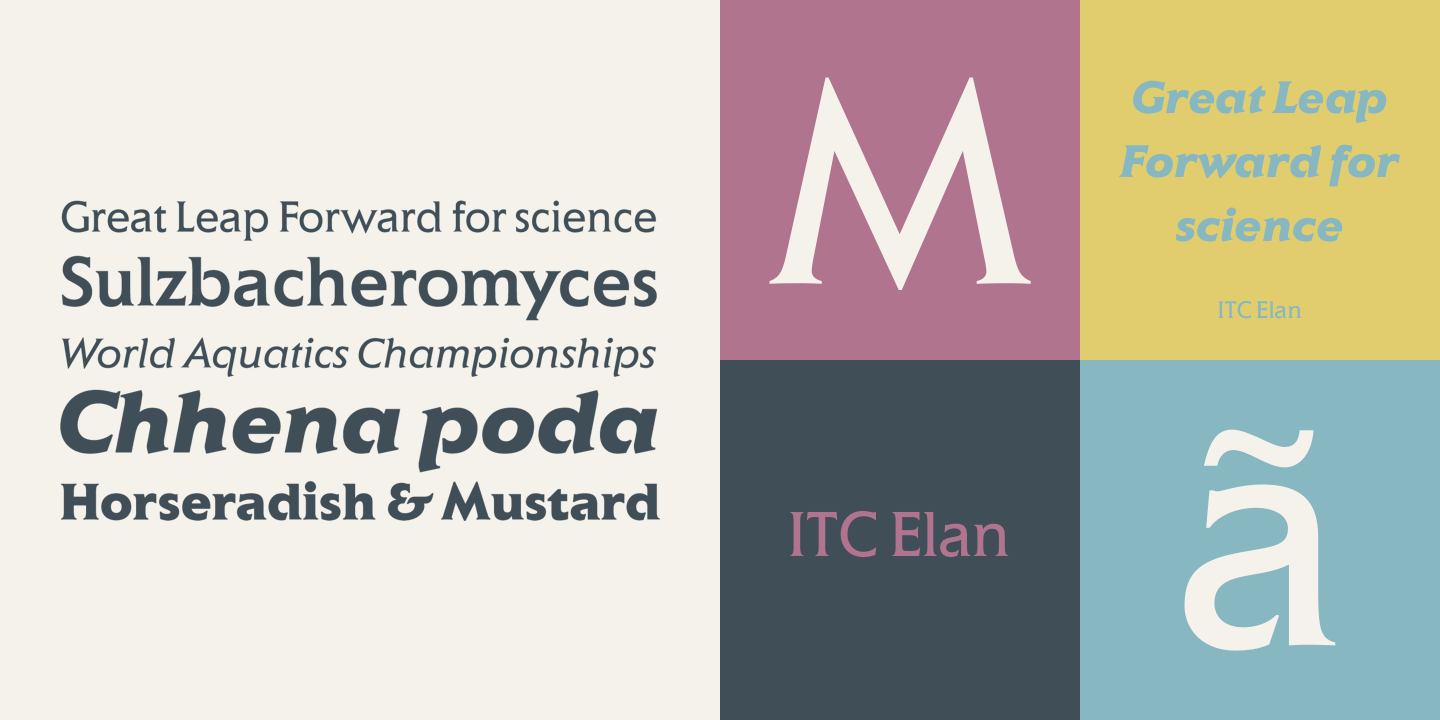
- 1985
- Antiqua humanistisch
Die ITC ist eine Antiqua-Familie von Albert Boton und erschien in den 1980er-Jahren als Fotosatzschrift über ITC und Berthold. Zum Familie zählen vier Strichstärken mit Kursiven. Alle Schnitte sind auch digital erhältlich.